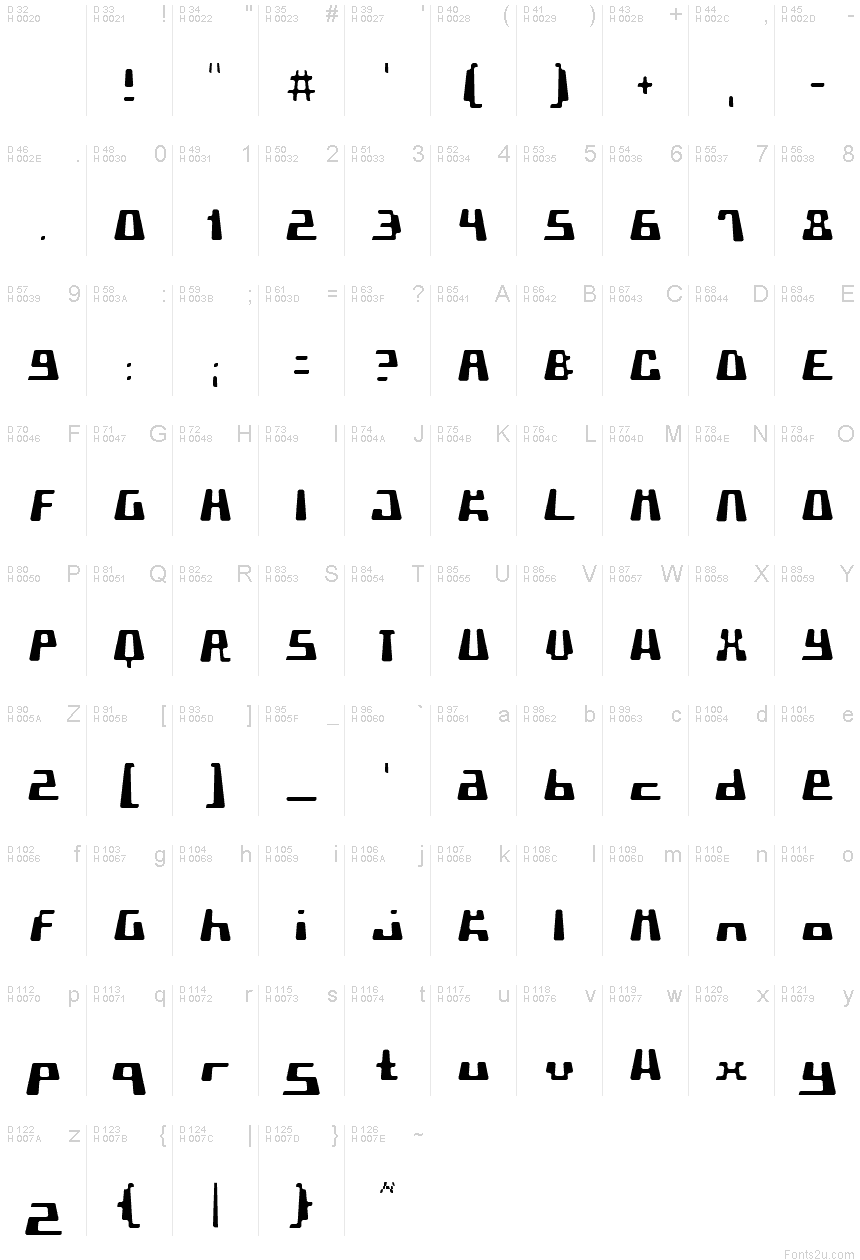
PormaskKlamd od TarmSaft font factory to darmowy krój displayowy w stylu wycinanki, o surowym, ręcznie wycinanym wyglądzie. Litery sprawiają wrażenie odciśniętych z miękkich czarnych kształtów, z zaokrąglonymi otworami, ściętymi rogami i lekko niezdarnym rytmem, co nadaje im zabawny charakter końca lat 90., zamiast wygładzonego, geometrycznego wykończenia.
Świetnie sprawdza się w nagłówkach plakatów, okładkach zinów, oprawie graficznej albumów, ulotkach klubowych i krótkich nazwach na opakowaniach, gdzie ten darmowy font o nieregularnej sylwetce potrafi przykuć uwagę. Użyj go, gdy potrzebujesz dużych słów, krótkich tytułów czy liter w stylu logo, które wyglądają na własnoręcznie zrobione i nieco dziwne – bo jego nierówne, „mięsiste” formy niosą ze sobą więcej klimatu niż technicznej precyzji.